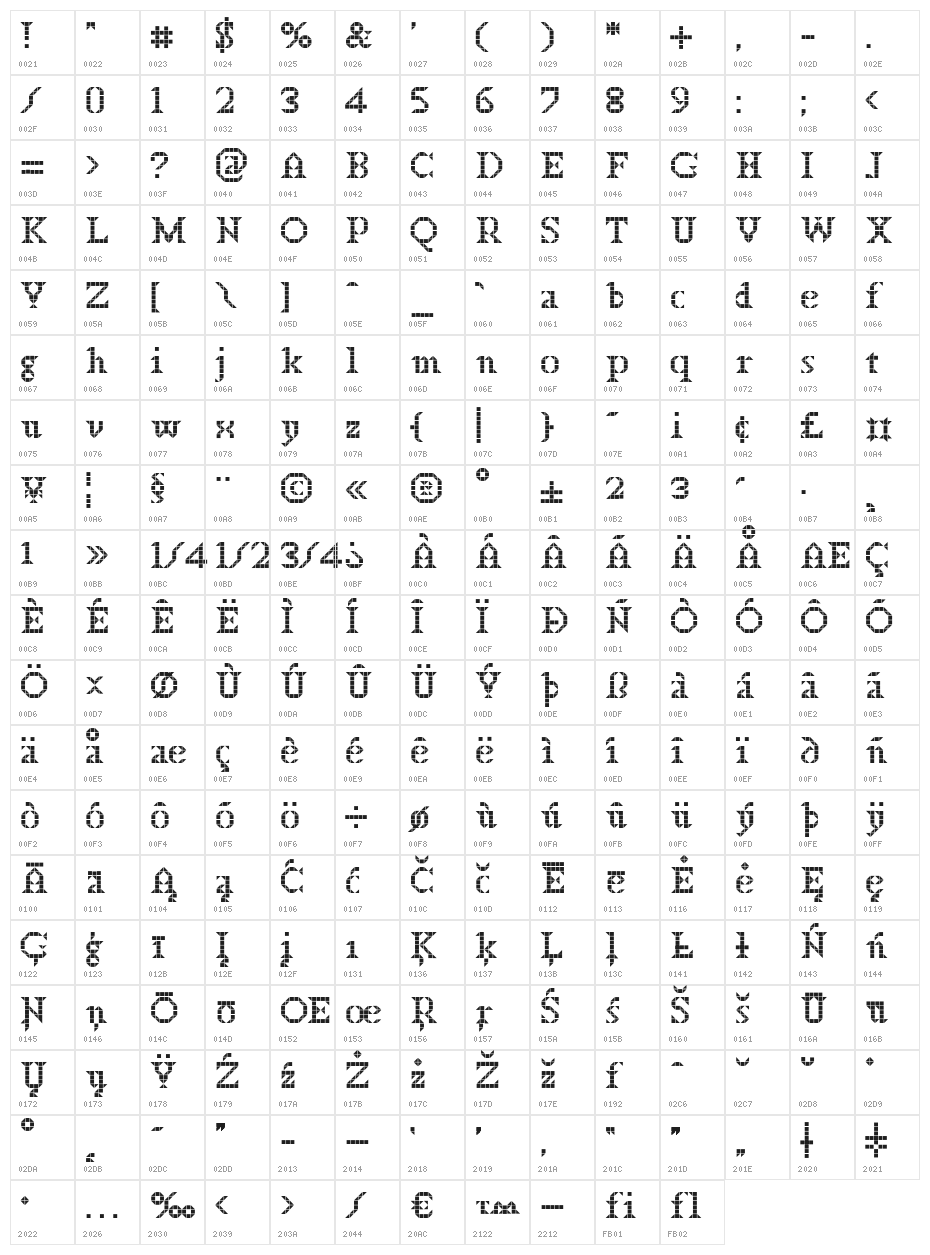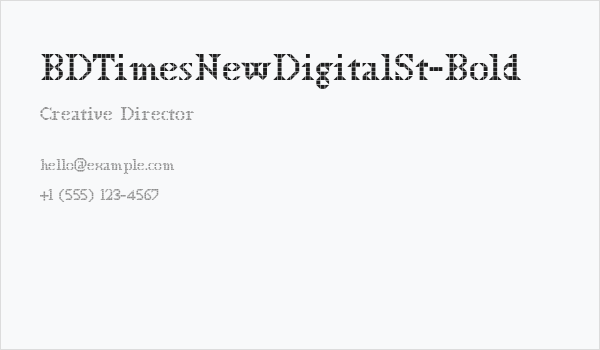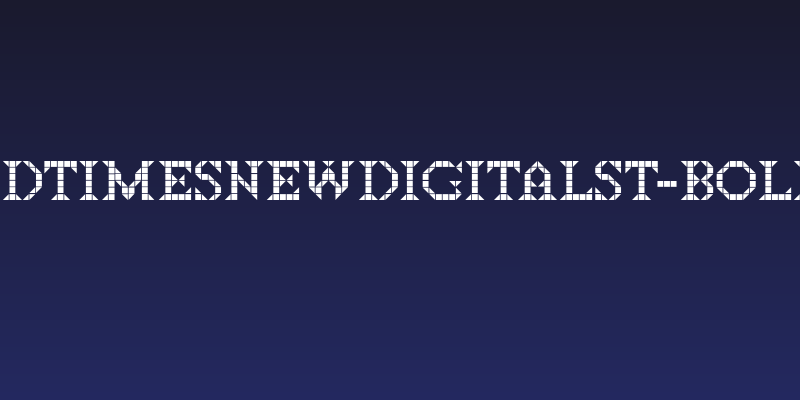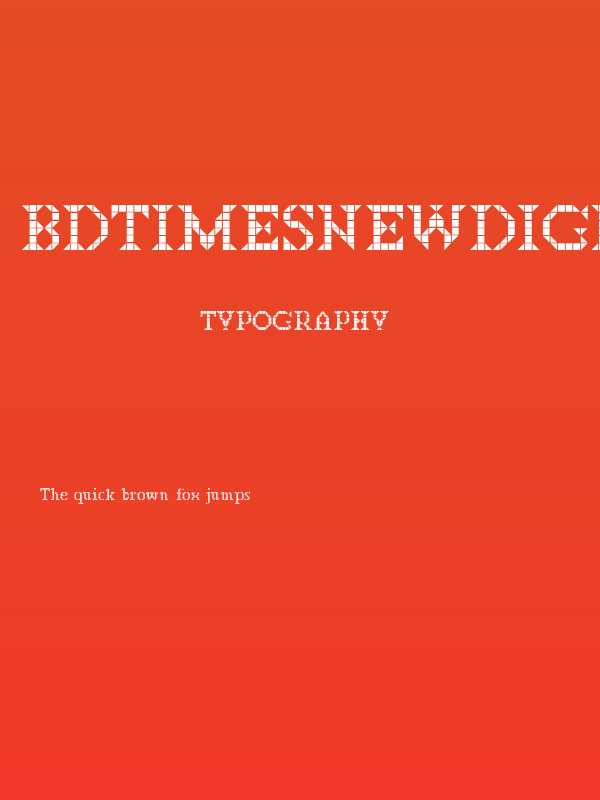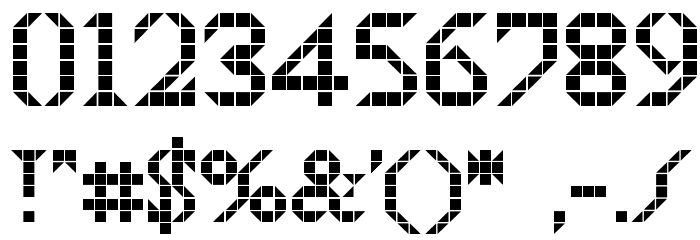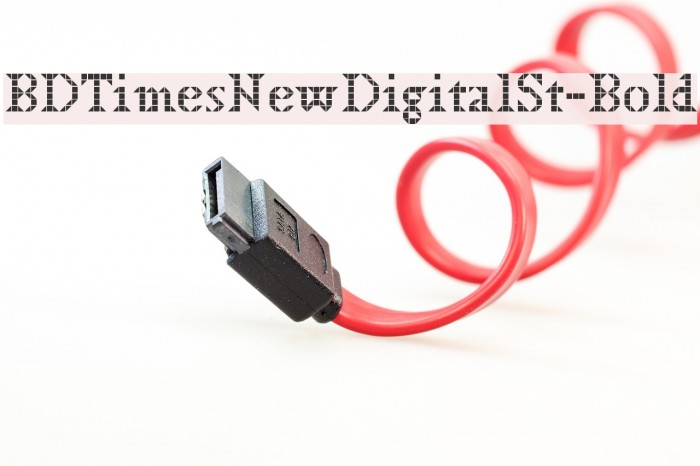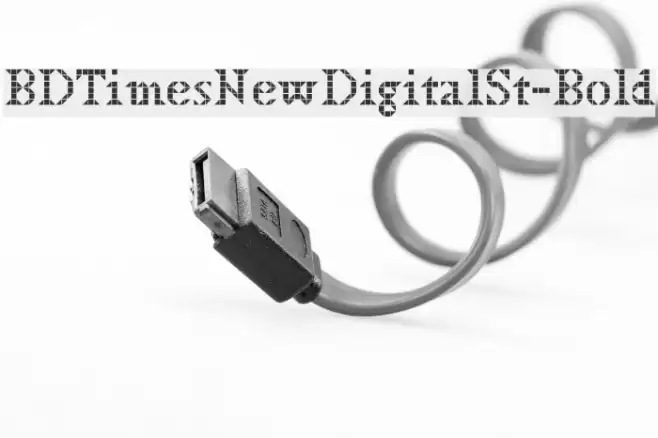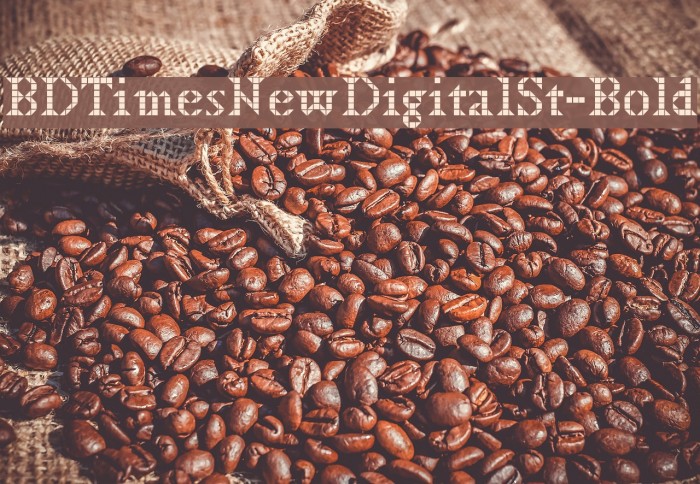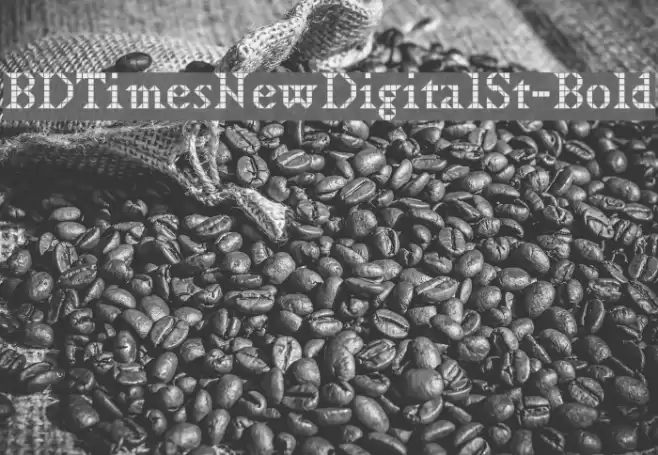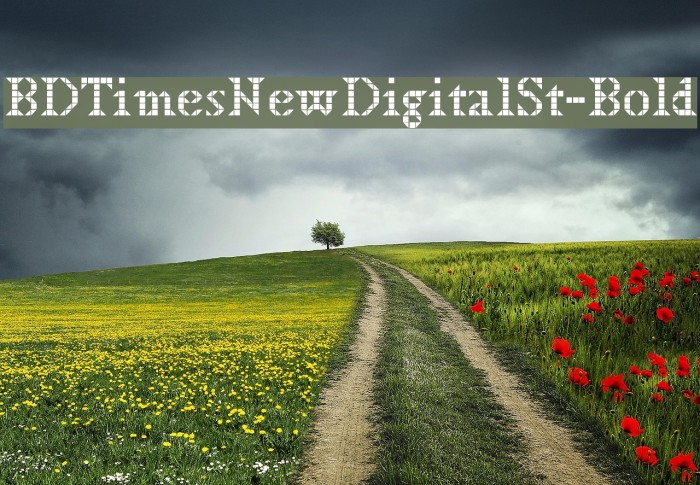
BDTimesNewDigitalSt-Bold Font
✎ Pixel
| नाम | BDTimesNewDigitalSt-Bold |
| वजन | Bold |
| श्रेणियाँ | Pixel |
| उपयोग का मामला | Headlines, Logos, Digital displays |
| सुझाए गए प्रोजेक्ट | Ideal for digital art, tech-themed posters, video game graphics, and futuristic branding. |